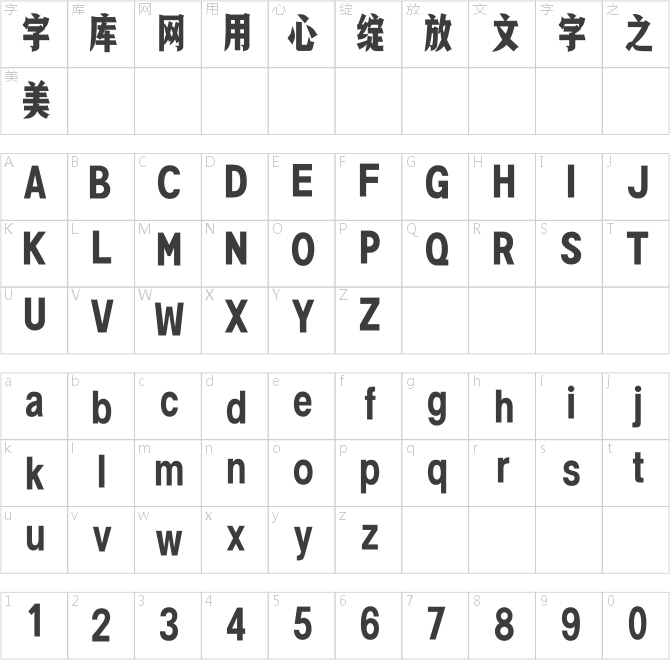
銳字澎湃簡 詳情頁
字體名稱: 銳字澎湃簡
作者版權(quán): 銳字潮牌
銳字澎湃簡
銳字澎湃簡字體字庫是一款讓人賞心悅目、百看不厭的中文字體,適合各類廣告和產(chǎn)品包裝設(shè)計應(yīng)用,字體大小1.59MB,格式為otf字體,上傳用戶是順新廣告?,作者/版權(quán)方為銳字潮牌